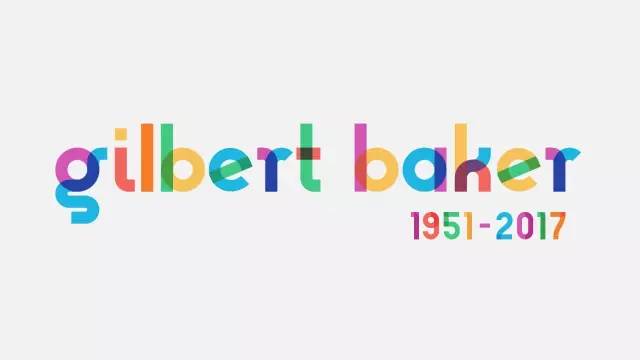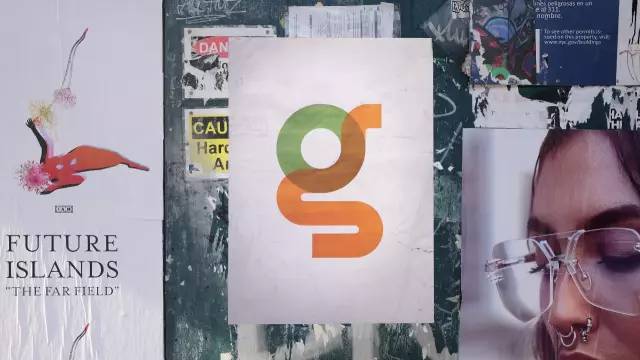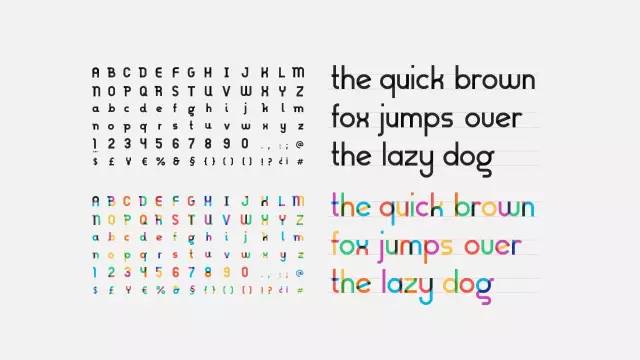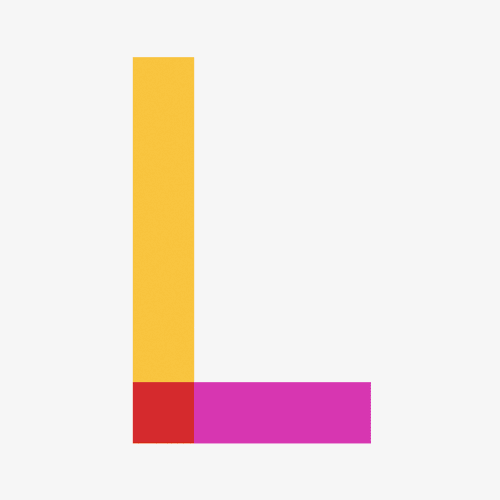
彩虹字体诞生了,彩虹字体的介绍、案例、设计灵感
彩虹旗的创造者 Gilbert Baker在 3 月 31 日于家中逝世,为了纪念 Gilbert 及其对 LGBTQ 群体的贡献,由 LGBTQ 公益组织 NewFest、NYC Pride,联合奥美广告及字体设计公司 Fontself 联合设计,将彩虹旗的设计语言转换成字体。字体的颜色都来自彩虹旗,在笔画相叠处半透明的设计组合成新的色彩。
Gilbert Baker 在 1978 年设计了彩虹旗,那时候正是酷儿运动如火如荼的年代,在他的好友、美国政坛中第一位公开同性恋身份的人 Harvey Milk 的请求与志愿者的帮助下,Gilbert 于旧金山的同志社区中心( Gay Community Center) 中手工上色、缝制了一面彩虹旗,并在 1978 年 6 月 25 日的游行中亮相。
最初彩虹旗有八个颜色,粉色代表性,红色代表生活、橘色代表治愈、黄色代表太阳、绿色代表自然、青绿色代表艺术、蓝色代表和平、紫色代表灵魂。
很快,这面旗变成了同志运动的标志,成功地成为被 LGBT 群体认可的身份标识。不仅出现在 LGBTQ 群体相关的组织和活动中,也为公司们表达政治正确,拉拢 LGBT 市场提供了一个便利的符号:衣服可以做成彩虹的,钥匙链可以做成彩虹的,冰箱上贴个彩虹旗也是对 LGBTQ 群体的支持。
奥美的设计团队说:“我们想要创作一种特殊的东西不仅仅是纪念 Gilbert 和它标志性的彩虹旗,也给 LGBTQ 群体一个制作自己 banner、海报和标识的工具。通过把彩虹旗融入到字体当中,我们让世界上每个人都可以‘骄傲地打字’”。彩虹字体会根据 LGBTQ 群体的反馈重新调整改进,整个过程将会在网络上公开记录下来。
推广彩虹旗的过程并不顺利,Gilbert 在采访中说:“人们不想听到彩虹旗,不想知道 gay 的旗帜是什么。很多别家的旗帜公司听到为 gay 生产旗帜完全震惊了,一些好一点的旗帜公司就是简单地不想知道关于 gay 的任何事情”。
为了在这个行业取得尊重和信誉,Gilbert 开始很努力地做一些大众意义上“有建设性”的设计,比如说为法国总统、 菲律宾总统 、委内瑞拉总统、西班牙国王等国家元首的公民活动设计旗帜和视觉。
直到 1994 年,Gilbert 移居纽约,开始将重心都投入到彩虹旗的再创作和同志平权运动中。